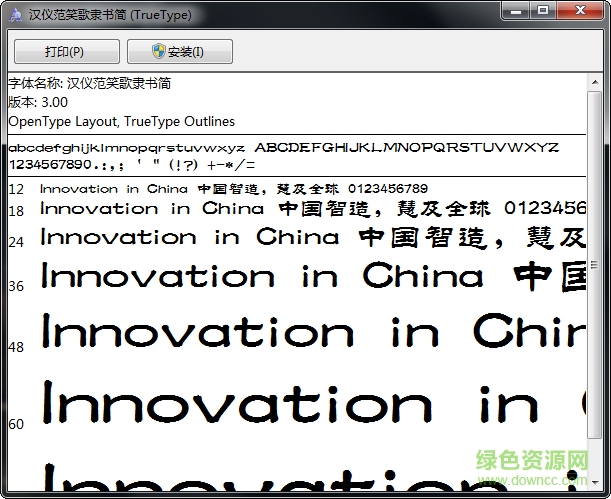
hys9gj是什么字體?hys9gj字體就是漢儀范笑歌隸書簡(jiǎn)體,這款字體筆畫疏密得當(dāng),剛?cè)嵯酀?jì),沉著得體,非常好看,歡迎大家在綠色資源網(wǎng)免費(fèi)下載!
隸書是漢字中常見的一種莊重的字體,書寫效果略微寬扁,橫畫長(zhǎng)而直畫短,講究“蠶頭燕尾”、“一波三折”。它起源于秦朝,在東漢時(shí)期達(dá)到頂峰,書法界有“漢隸唐楷”之稱。也有說法稱隸書起源于戰(zhàn)國時(shí)期。
漢隸主要有兩大存在形式:石刻與簡(jiǎn)牘。魏晉南北朝隸書大多雜以楷書筆法;唐朝隸書不乏徐浩等書家。宋元明三朝的隸書也難振漢隸雄風(fēng)。直至清朝。漢隸才得以復(fù)蘇。有金農(nóng)、鄧石如、何紹基等,別有建樹。